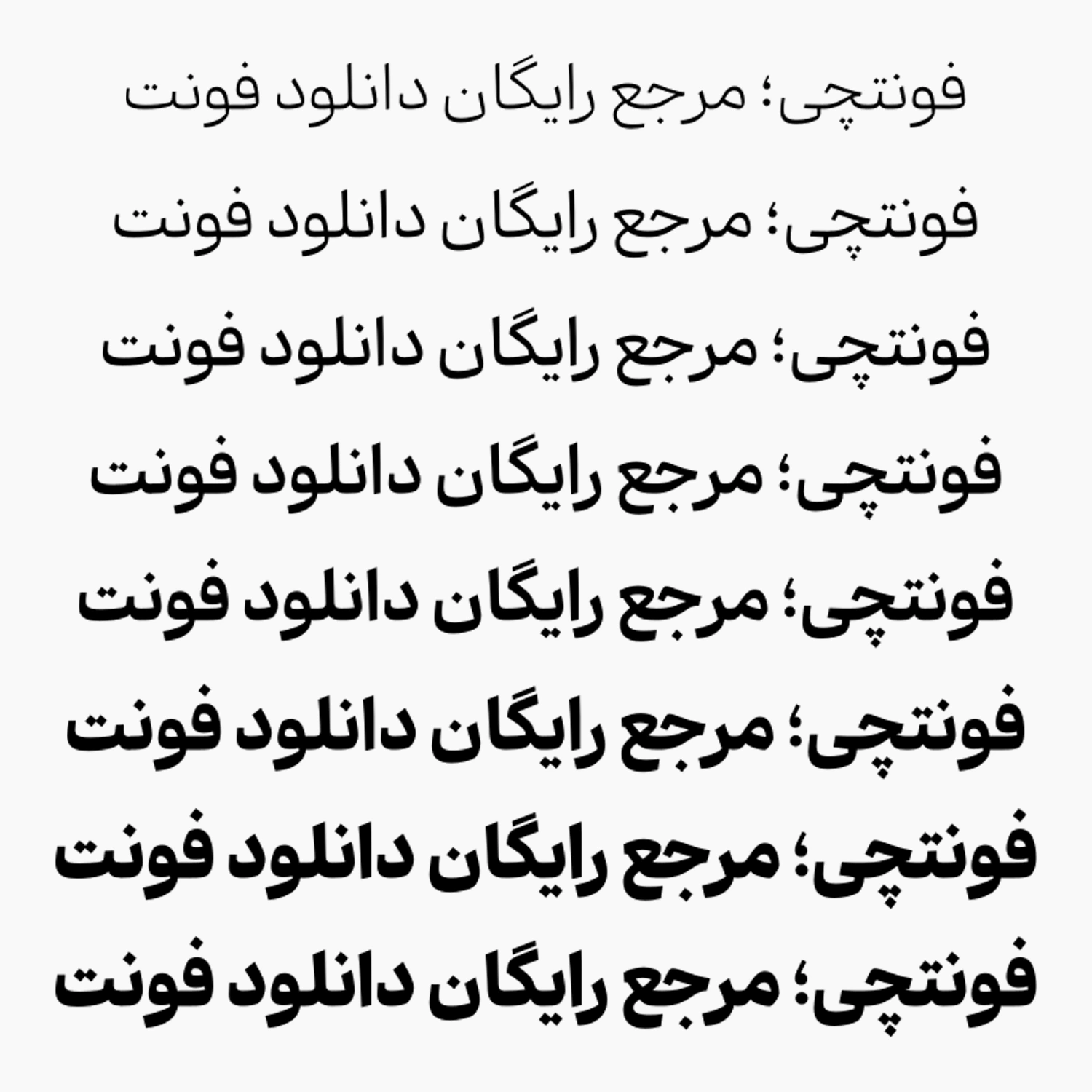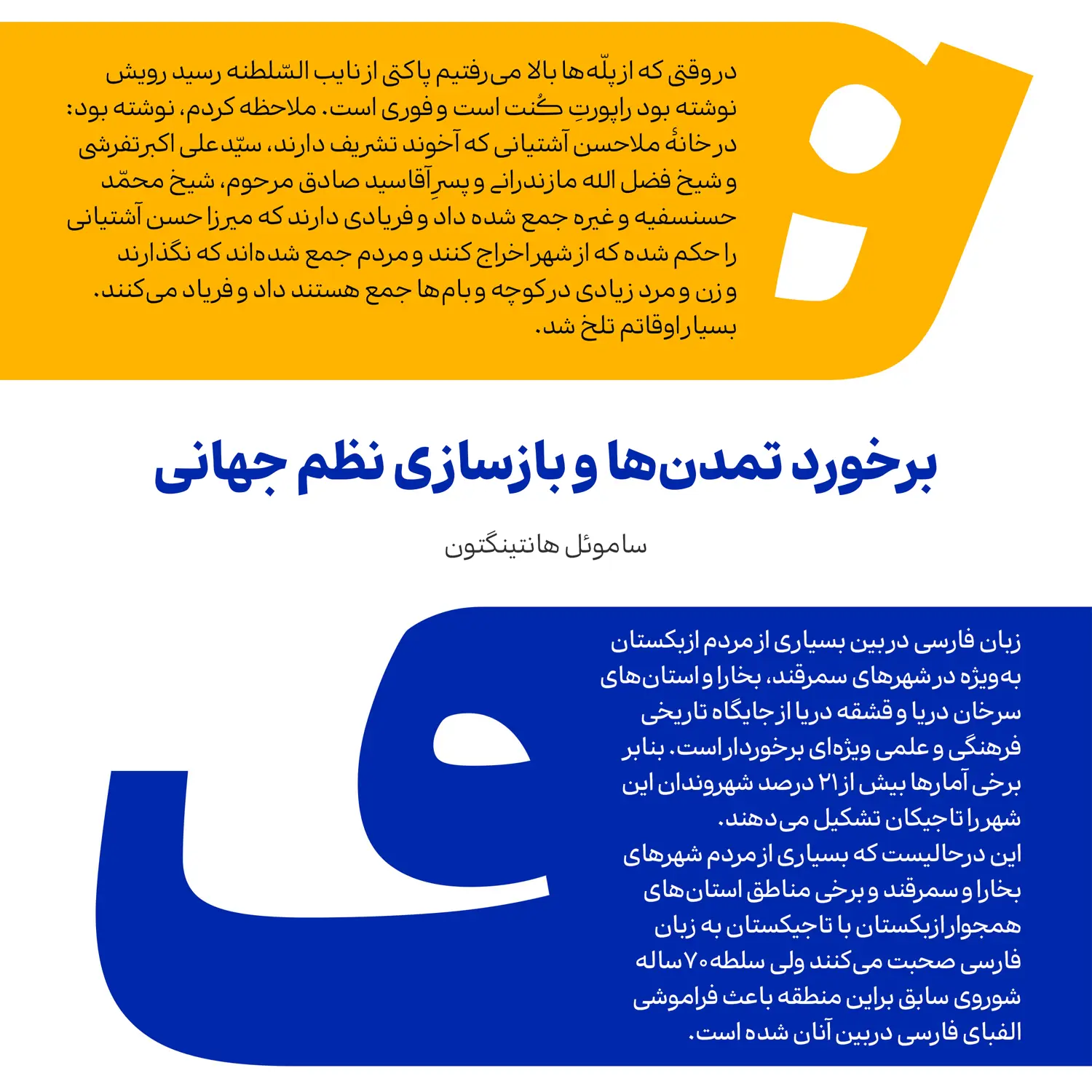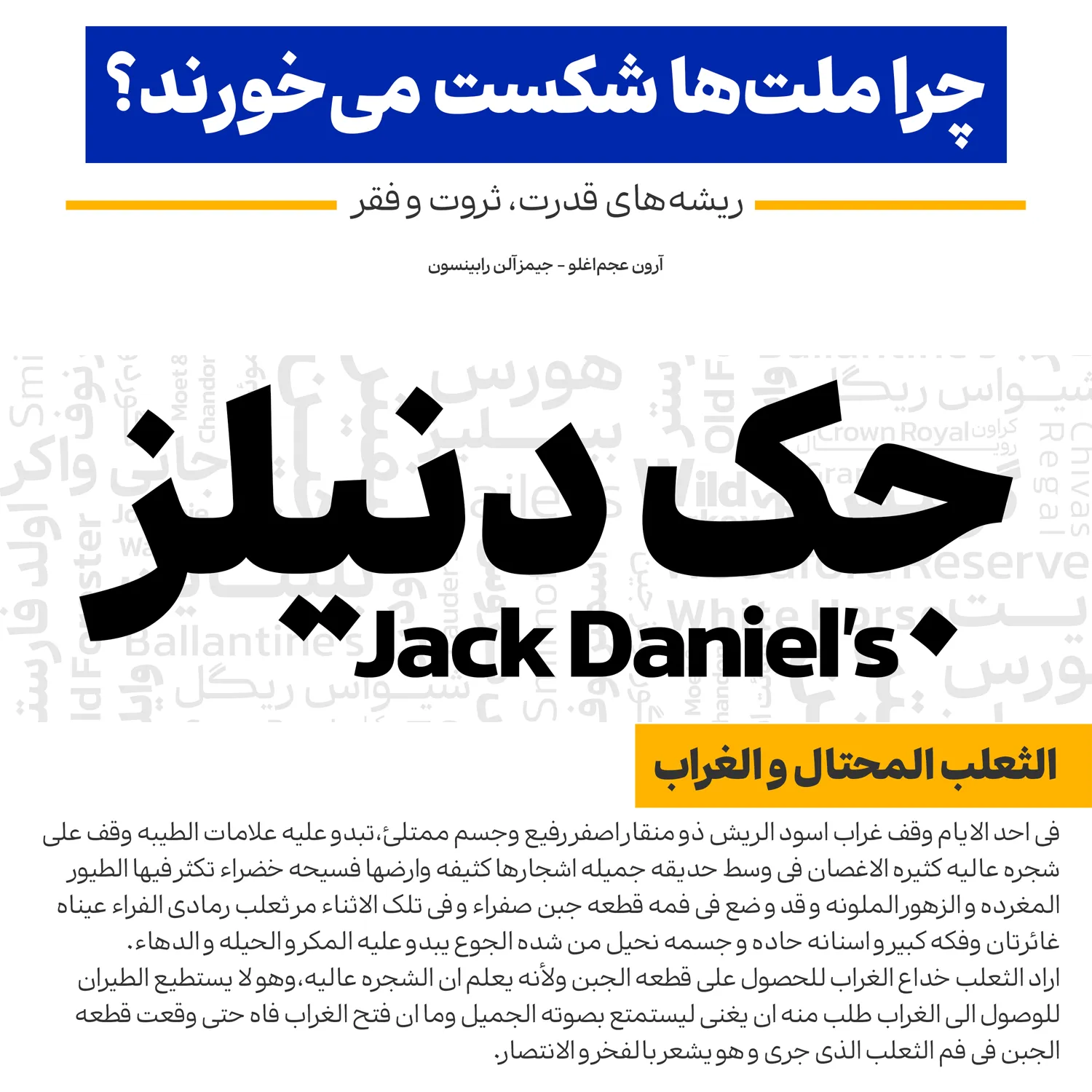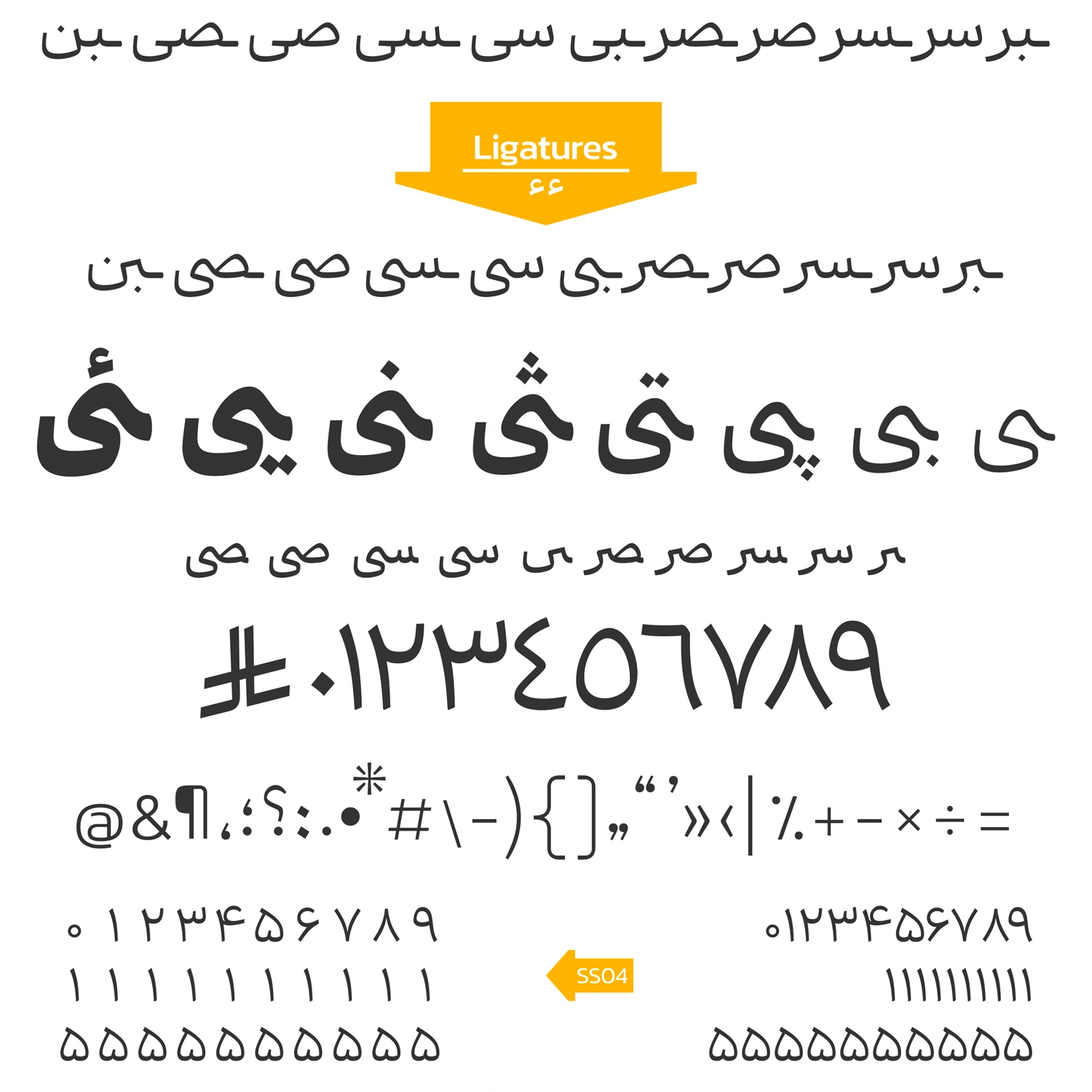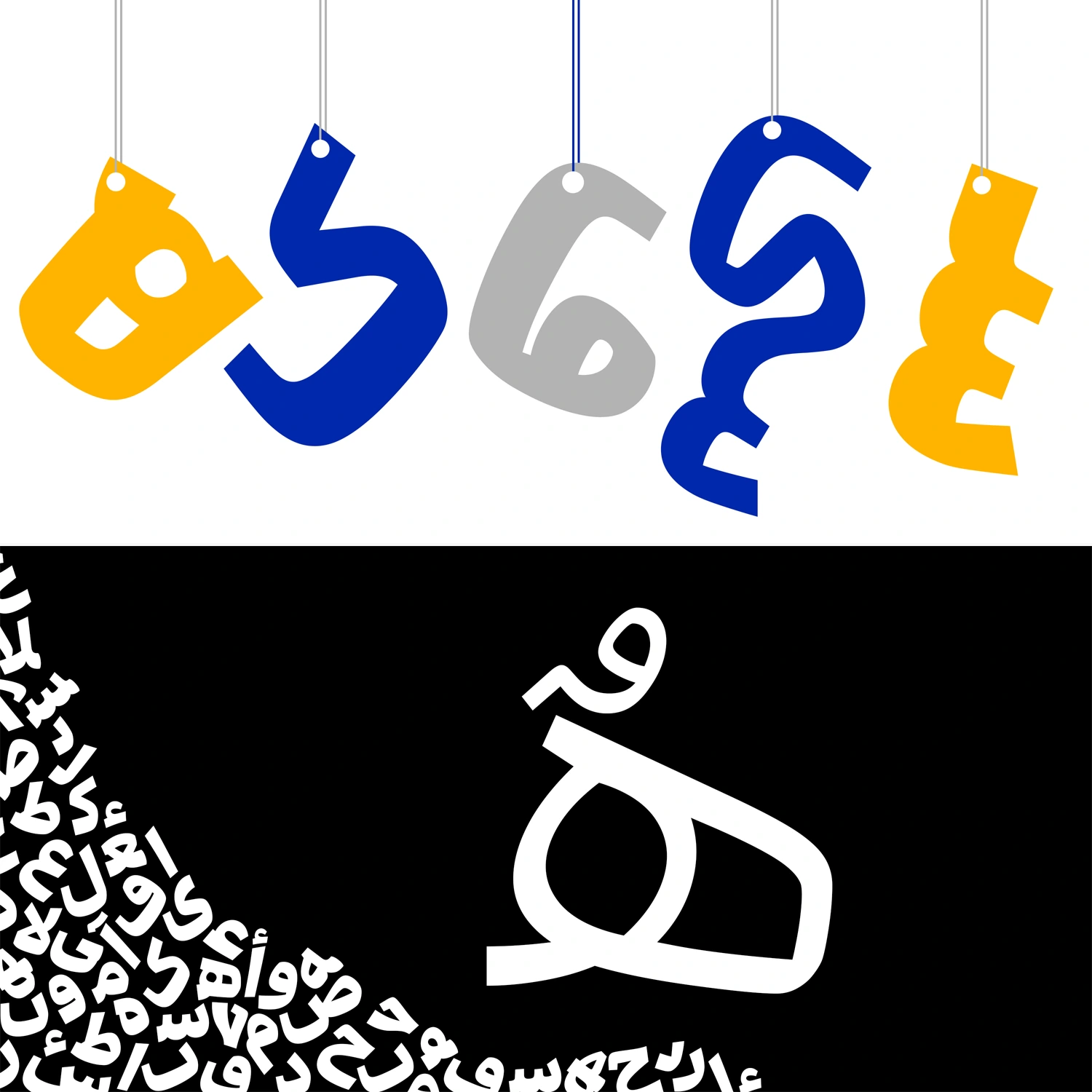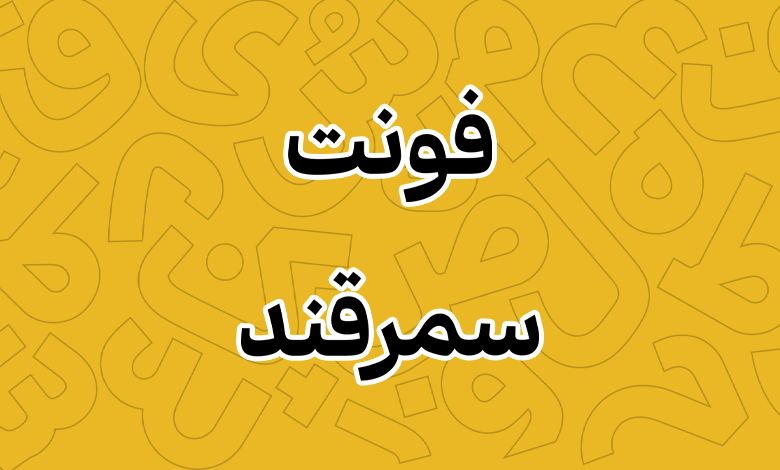
فونت سمرقند (Samarqand)
فونت سمرقند (به انگلیسی: Samarqand) حاصل نگرشی دگرگونکننده به سنت تایپوگرافی معاصر است. رضا بهلول در این اثر تلاش کرده تا پیوندی بین استخوانبندی و ریتم آشنای خط نسخ با جریان مدرن دیجیتال امروز ایجاد کند. نقطهعطف این طراحی، ساخت رویکردی تک ضخامتی (Monoline) یا نیمه مونولاین در فرمپردازی حروف است.
این تکنیک باعث شده تعادل بصری بین ضخامت خطوط افقی و عمودی برقرار شود و فونت از محدودیتهای کنتراست شدید کالیگرافیک (که معمولا در نسخ سنتی دیده میشود) فاصله بگیرد. در نتیجه، شخصیت بصری سمرقند هویت «معماریگونه، منسجم و شفاف» پیدا کرده است.
با بررسی جزئیات گرافیکی و ساختار حروف بر اساس تصاویر میتوان به چند ویژگی کلیدی که بیش از پیش خودنمایی میکنند رسید.
دندانهها و فضاهای منفی (Counters) ساختار چشمها و حلقهها (نظیر حروف «ع»، «ص»، «م») به گونهای باز و گسترده طراحی شده است. این فضای منفی، مانع از سیاهی و خستگی چشم هنگام خواندن در ابعاد کوچک میشود. از طرفی دیگر در اندازههای بزرگ نیز خود را به خوبی نشان داده و موجب جلب توجه بیشتر خواهد شد. هر چند که بسته به وزن انتخابی، تناسب و میزان این دندانهها متفاوت هستند.
کشیدگیها و زوایا دارای دورها و قوسهای نرم محل اتصال حروف، ریتم روان و شناوری ایجاد کردهاند. زاویههای ملایم در گوشهها بدون شکسته شدن ساختار کل، لحنی مدرن اما صمیمی به متون میبخشد.
برخلاف فونتهای سنتی رایج که در وزنهای بالا با افت خوانایی روبهرو میشوند، سمرقند در وزنهای سنگین، فرم حروف را فشرده نکرده بلکه با حفظ تناسبات، وزن بصری قدرتمندی برای تیترها خلق میکند. به عبارتی دیگر ساختار و شکل حروف در وزنهای مختلف این فونت از تناسب خاص خود برای چشمیها، زوایا و دندانهها برخوردار هستند که باعث میشود هم برای طراحی رابط کاربری و هم مطبوعات بهترین انتخاب باشد.
سمرقند صرفا فونتی نیست که بخواهید به سادگی از آن در کارهای گرافیکی و متون استفاده کنید. این فونت وریبل که امکان تغییرات وزنی را در یک فایل فونت برای همه وزنها میدهد، هنگام استفاده در برنامههایی مانند فتوشاپ و ایلاستریتور، دست شما را برای طراحی بازتر خواهد گذاشت. با استفاده از تنظیمات Stylish Set میتوانید موارد زیر را کنترل کنید:
- SS01 & SS02: با فعال کردن این گزینه فرمهای جایگزین برای حروفی مثل «ی» کشیده یا «ک» با ساختار کشیدهتر ایجاد میشود.
- SS03 & SS04: دسترسی آسان به جدول اعداد انگلیسی/عربی به اعداد همعرض و همتراز فارسی (Tabular Figures) که برای جداول، فاکتورهای مالی و رابطهای کاربری بسیار ضروری است.
- علامتهای تجاری و ارزها: پشتیبانی از کاراکتر اختصاصی واحد پولی ریال (همچون ریال عربستان) و نشانههای محاسباتی کاملا هماهنگ.